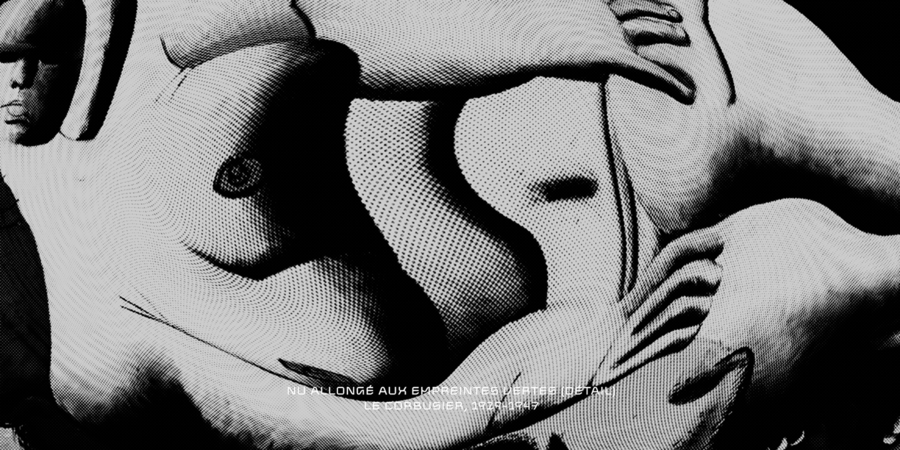
Gik (3 шрифта)
Gik – це сімейство шрифтів без зарубок з модульною естетикою та елегантністю сучасної типографії. Його композиційно-пластичне рішення поєднує в собі відгомони (де)конструктивізму, бруталізму, де Стилю та інших проявів античності 20 століття + прийоми, характерні для курсиву. Але це не робить шрифт старомодним – навпаки, допомагає зрозуміти, як ним користуватися.
Gik є продуктом епохи метамодернізму – він знаходиться на межі між модерністським ентузіазмом і постмодерністським знущанням, між простотою і усвідомленістю, цілісністю і розщепленістю, ясністю і багатозначністю – такий собі концептуальний оксюморон. Дивлячись на Gik, можна було б уявити його на Тижні Моди, якби такий існував для шрифтів. Gik має послання як для дизайнера, так і для глядача, він стимулює уяву, це антологія всіх шрифтів майбутнього. Шрифт розробив Денис Серебряков у 2022 році.
Асоціації з сімейством шрифтів GikОсобистість і характер гарнітури:
рівний, точний, холодний, автоматичний, техногенний, прямокутний, міський, сучасний, машинний, гострий, інженерний, урбаністичний, скляний, крихкий, футуристичний, дротяний, космічний, електронний, комп'ютерний, іронічний, дивний, гнучкий, динамічний, неоновий, тонкий, ламаний, худий, самобутній, оригінальний, характерний, грайливий, цікавий, психоделічний, прозорий, інопланетний, твердий, чіткий, стійкий, сталевий, молодіжний, тусовочний, клубний, двіжняковий, нічний, індустріальний, штучний, технічний, якісний, залізний, незграбний, лаконічний, гладенький, сильний, промисловий, впевнений, крутий, амбітний, креслярський, архітектурний, грубий, брутальний, суворий
конструктор, креслення, архітектура, інженер, автоматика, урбаністика, наука, дизайн, Місто, гаджет, електроніка, технології, фантастика, космос, інновації, інтернет, девайс, айтішник, айті, IT, комп'ютер, робот, андроїд, головокрутка, техніка, прилад, мобільний зв'язок, інструмент, гра, залізо, рентген, нічний клуб, вечірка, тусовка, комп'ютерна гра, верстат, завод, промисловість, електростанція, енергетика, хакер, код, програмування, танець, дискотека, авто, кубики, розваги, реп, концерт, кіберспорт, архітектор Гарнітура має ознаки стилів: